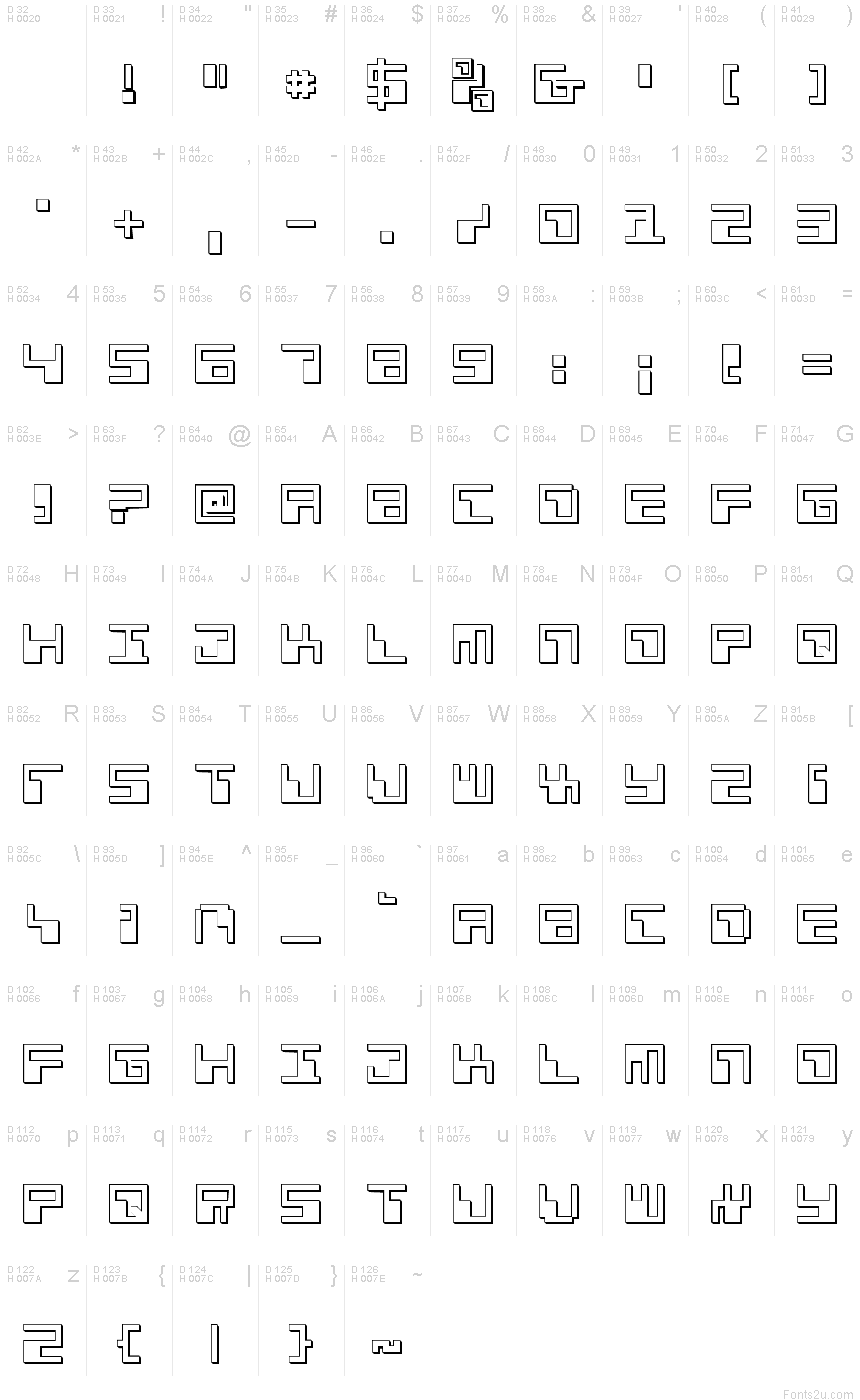
Phaser Bank 3D od Iconian Fonts to darmowy, futurystyczny krój 3D, składający się z samych wielkich liter, utrzymany w surowym, modularnym klimacie dawnych logotypów science-fiction. Znaki zbudowano na bazie kwadratowych narożników i szerokich wycięć, otaczając je blokowym obrysem, co nadaje całości masywnej, niemal przemysłowej głębi.
Naturalnie odnajduje się w brandingu gier arcade, ekranach tytułowych, nagłówkach plakatów, grafikach eventów technologicznych i okładkach komiksów, gdzie krótkie hasła potrzebują wyrazistego, trójwymiarowego efektu. Jako darmowy font, sprawdzi się również w tytułach i monogramach, szczególnie gdy zależy Ci na tym, by wielkie litery sprawiały wrażenie „skonstruowanych”, a nie wygładzonych.